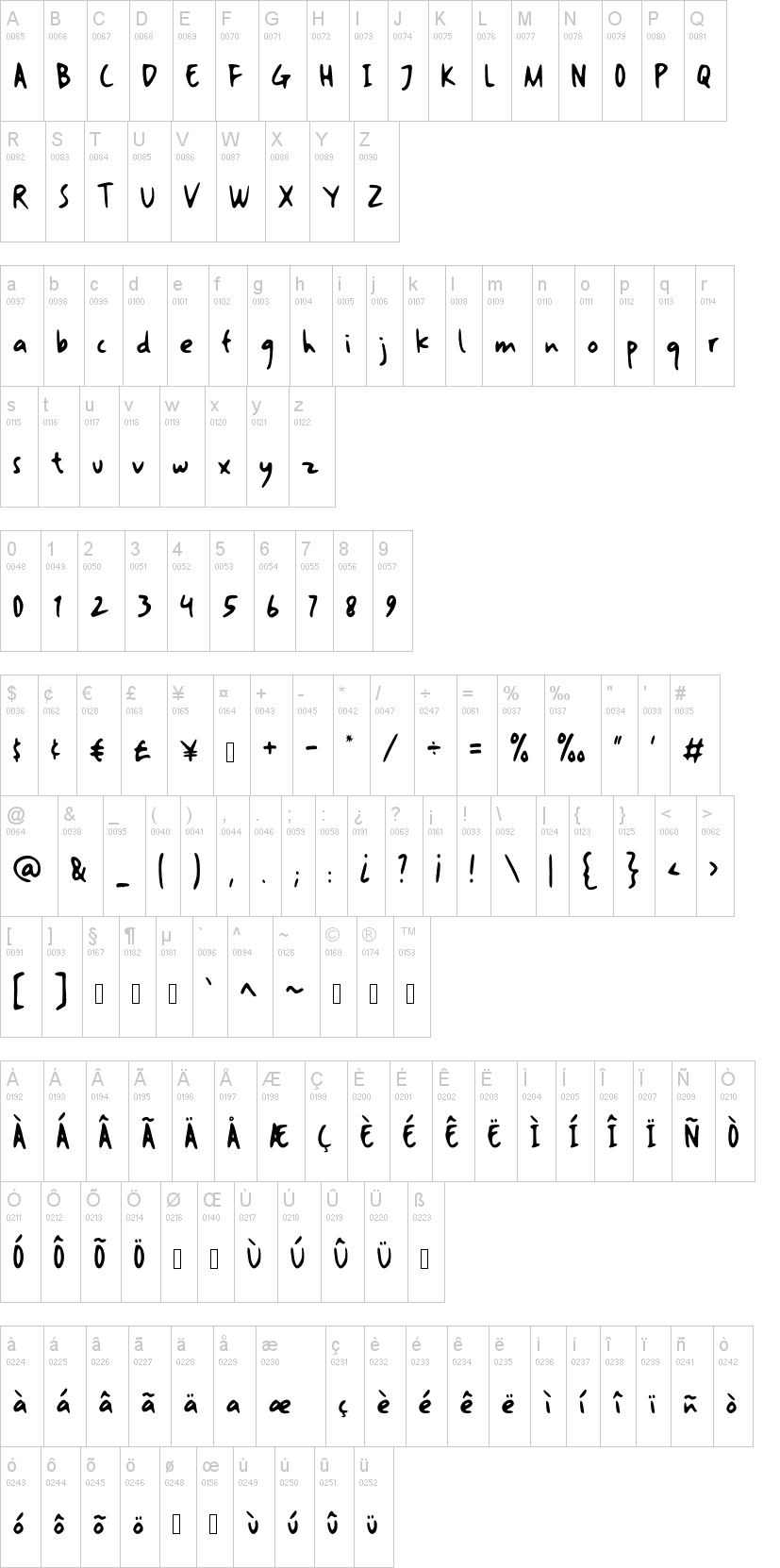
Artomoro
Artomoro 是一款来自印度尼西亚设计师 Adien Gunarta 的美丽艺术字体。这种字体的风格是古老的印度尼西亚文化与现代设计元素相结合的产物。Artomoro 字体具有流畅的线条和华丽的点缀,适合用于标题、印刷品和海报等设计项目。此外,Artomoro 字体具有多种变体,包括常规、粗体、斜体和粗斜体,可以满足各种设计需求。如果您正在寻找一款充满艺术气息的字体,Artomoro 可能是一个不错的选择。
Artomoro是一款非常不错的手写艺术字体,具有很好的视觉感,适合于文化类的宣传设计、商业类品牌的广告和产品包装设计以及个性化文字排版等较多场景。